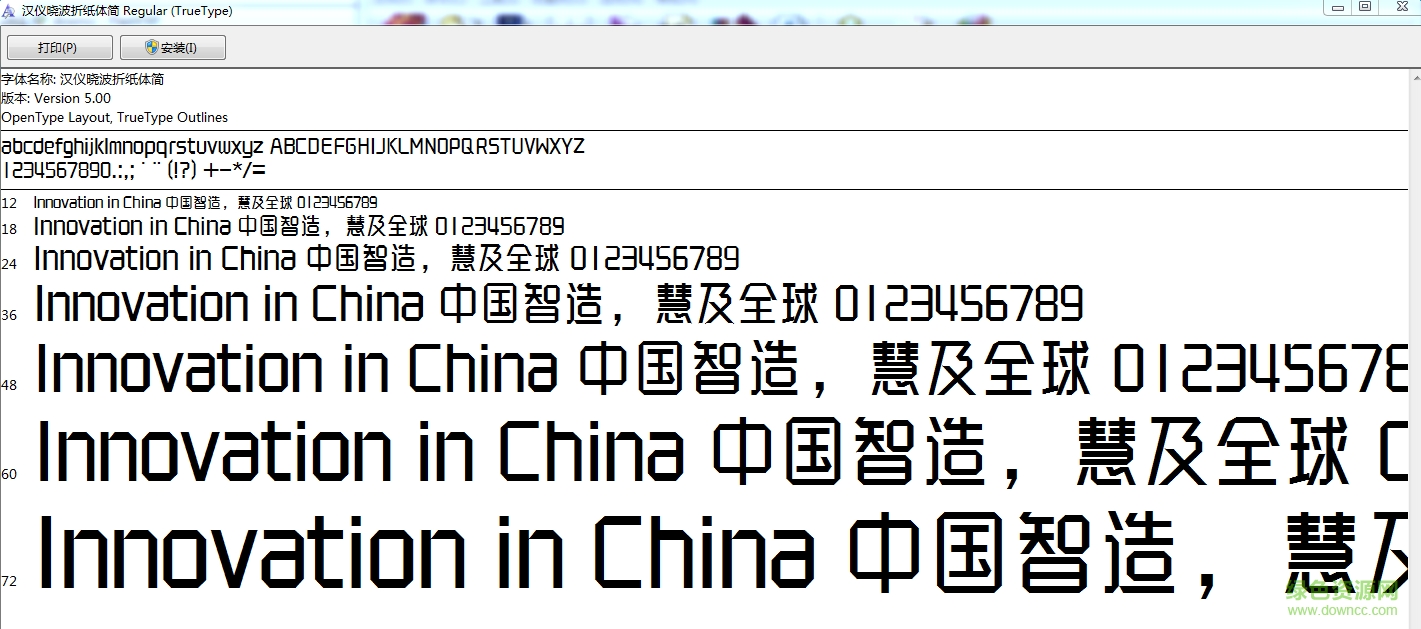
漢儀曉波折紙?bào)w
漢儀曉波折紙?bào)w簡字體是一款漢儀類折紙風(fēng)格字體軟件,折紙?bào)w字體給人非??犰湃A麗的感覺,盡顯文藝范,深受廣大書法家和年輕人的喜愛,還有更多好看字體盡情期待,歡迎到綠色資源網(wǎng)下載體驗(yàn)!
字體介紹
漢儀曉波折紙?bào)w字體筆畫連接如同折紙,每個折角都處理成紙張折疊效果,設(shè)計(jì)師可以用它實(shí)現(xiàn)想要的拉伸和切割效果,折紙?bào)w會很好的視覺呈現(xiàn).瘦高的比例也使它在具有時尚高挑的現(xiàn)代感同時,又有很強(qiáng)設(shè)計(jì)感和趣味性。